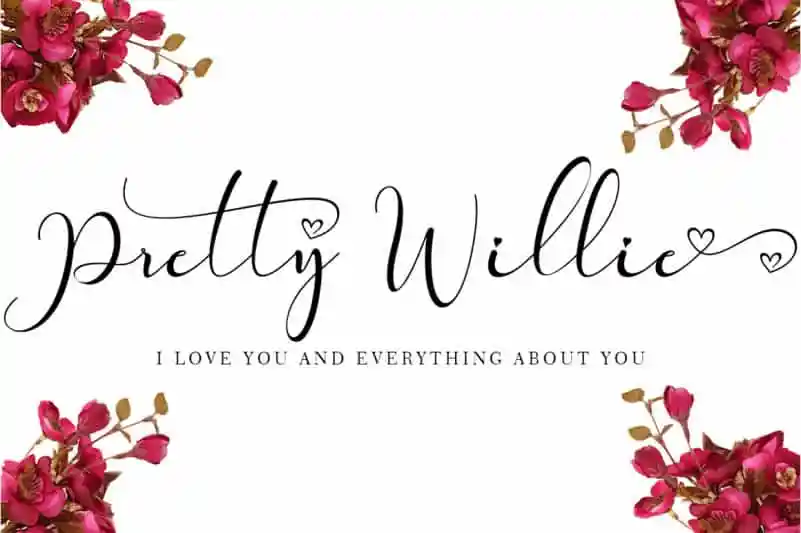
A fonte Pretty Willie Calligraphy Font é uma criação moderna e romântica que oferece um toque especial a qualquer trabalho que você faça. Inspirada na autêntica arte do desenho frondoso, essa fonte traz uma qualidade única, perfeita para decorar seus projetos de forma elegante e sofisticada. Desenvolvida em condições agradáveis e românticas, incluindo o carinho de uma esposa amável que sempre oferece suporte, ela se torna um recurso indispensável para todos os seus projetos relacionados à celebração matrimonial. Esta fonte é perfeitamente adaptada para criar cartões de aniversário e convites nupciais, assim como para expressar seu amor e sentimentos para aqueles que ama. Ela também é ótima para criar uma identidade visual para sua empresa ou marca online em meio a ambientes socialmente conectados e profissionais, sem perder o toque pessoal e emocional que a chamada para o casamento sempre deve conter.